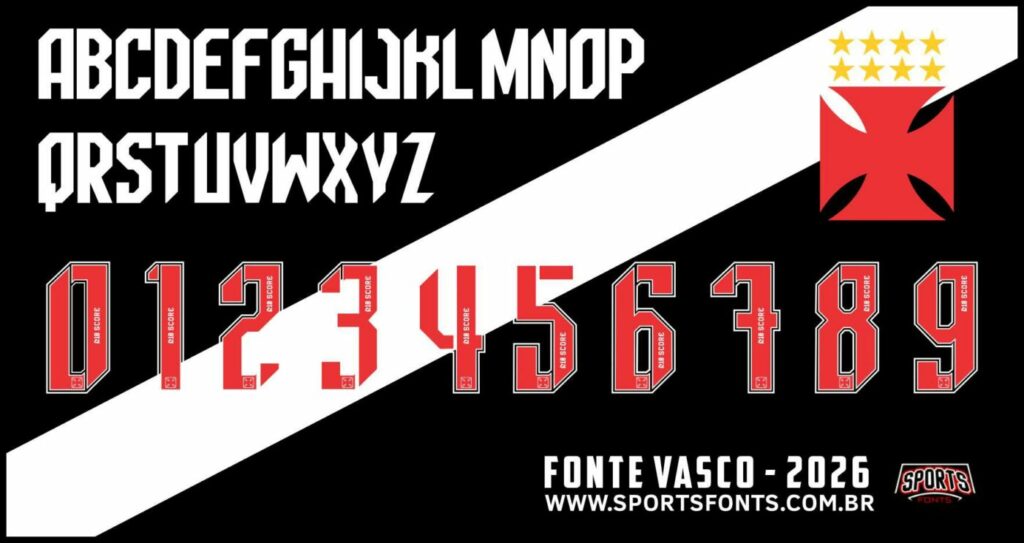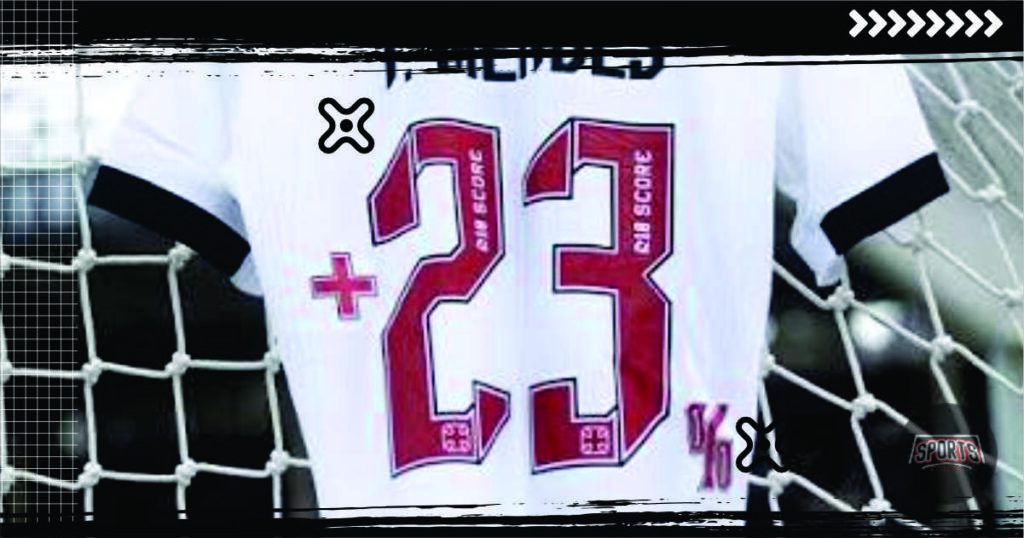
Se você procura a fonte Vasco da Gama 2026 para personalização de camisas, uniformes esportivos ou projetos gráficos, chegou ao lugar certo! Aqui você encontra a tipografia completa do Gigante da Colina, pronta para uso em vetor e instalável.
A nova tipografia desenvolvida para a temporada de 2026 do Vasco une a tradição da Cruz de Malta a uma estética moderna e agressiva.
- Letras (A–Z): Design em caixa alta com cortes angulares marcantes e inspiração levemente gótica, combinando perfeitamente com a identidade histórica do clube.
- Números (0–9): Numeração estilizada em destaque (vermelho com contorno branco e detalhes tridimensionais).
- Selo Exclusivo: Conta com a aplicação interna da marca R10 SCORE nas barras verticais dos números, garantindo fidelidade total ao modelo de jogo.
Como de costume, aqui na Sports Fonts, realizamos o processo de vetorização detalhada para entregar uma versão fiel e de alta qualidade dessa tipografia. Nosso objetivo é fornecer um material de referência para designers que trabalham com mockups, artes esportivas e personalização de conceitos, sempre prezando pela precisão das formas e espaçamentos originais.
- Elementos: Alfabeto Completo e Numeração
- Destaque: Detalhes internos preservados para aplicação em qualquer cor.